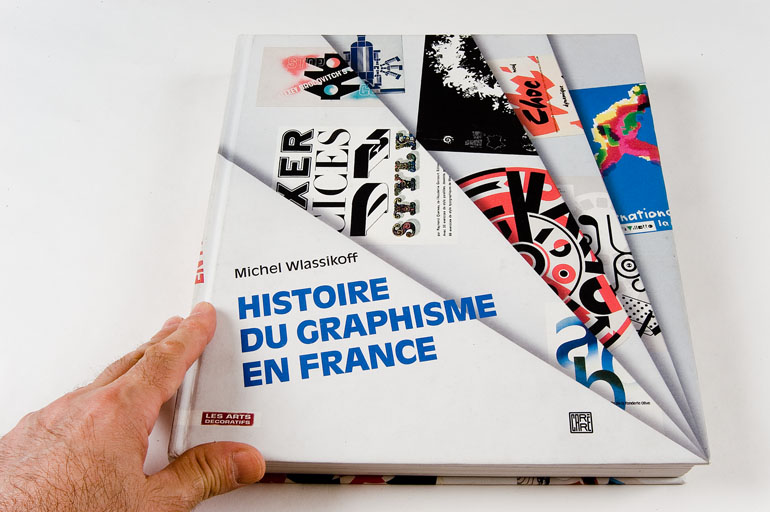
Graphisme et typographie
(des origines à nos jours)
par Michel Wlassikoff, historien du graphisme
et rencontrer Michel Wlassikoff qui nous conte
l’«Histoire du graphisme en France… et ailleurs»
Prédominance
de la langue et
de la typographie françaises
du XVIe au XIXe siècle.
Michel Wlassikoff, historien du graphisme, auteur d’Histoire du graphisme en France – Diplômé de l’École des hautes études en sciences sociales (EHESS), Michel Wlassikoff a dirigé Signes, revue de référence consacrée au graphisme; il est l’auteur d’ouvrages historiques dans ce domaine (notamment Histoire du graphisme en France, Musée des arts décoratifs, 2005, réédition en 2008). Commissaire d’expositions («Signes de la collaboration et de la résistance», ÉSAD Strasbourg, 2000 ; «Signes», Centre Pompidou, 2001, 2002, 2003), il participe aux Revues parlées sur le graphisme au Centre Pompidou, et enseigne l’histoire du graphisme au sein de plusieurs écoles supérieures d’art.
Ce cycle de conférences suit un parcours historique, des origines à nos jours. S’appuyant sur une vaste iconographie, Michel Wlassikoff décrit et définit les différents aspects de la pratique du graphisme : art de l’affiche, création typographique, graphisme éditorial, graphisme de presse, graphisme d’information, graphisme multimédia, habillage télévisuel…
Les évolutions du graphisme et de la typographie sont examinées en lien avec les arts plastiques, la photographie, le design et l’urbanisme. L’objectif est de développer une réflexion sur l’évolution du rapport entre le texte et l’image et sur la place du graphisme dans les systèmes de communication et en tant que pratique artistique et sociale.